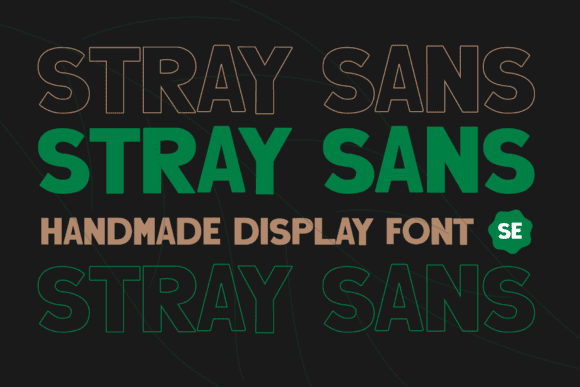
Название: Stray Sans Font
Stray Sans - это классный, смелый и толстый шрифт.
Независимо от темы, этот шрифт будет невероятно полезен в вашей библиотеке шрифтов, поскольку он способен приподнять любое творение.